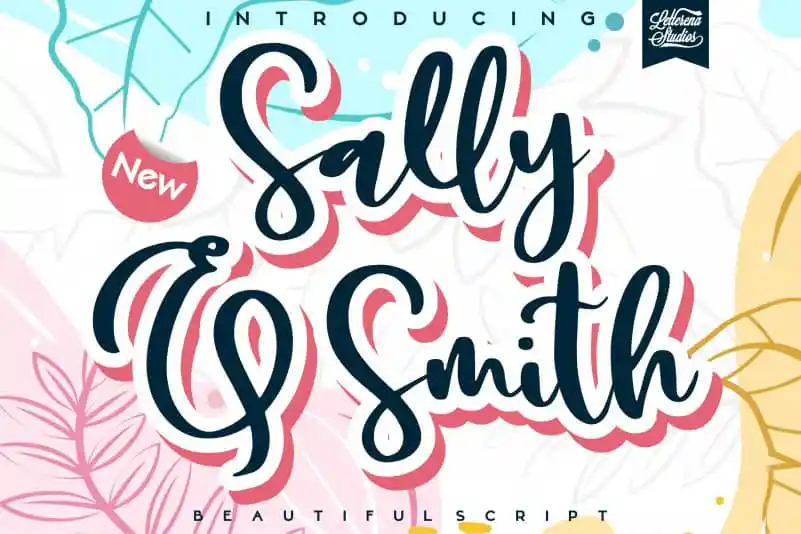
Sally & Smith Script Font – Download Grátis
Sally & Smith Script Font é uma fonte escrita a mão romântica e sedutora, perfeita para quem busca personalidade em seus projetos visuais. Esta fonte PUA (Private Use Area) está disponível de forma conveniente, permitindo que você acceda facilmente a todos os gílios e estilos chamativos. Este design único é ideal tanto para letras e títulos quanto para materiais de escrita, garantindo um toque autêntico que se destaca em uma variedade de ideias criativas. Ideal para aqueles que valorizam personalização, Sally & Smith Script Font oferece o contraste perfeito entre a simplicidade do estilo e a elegância das suas formas delicadas, tornando-a uma escolha atraente para todos os projetos de design.